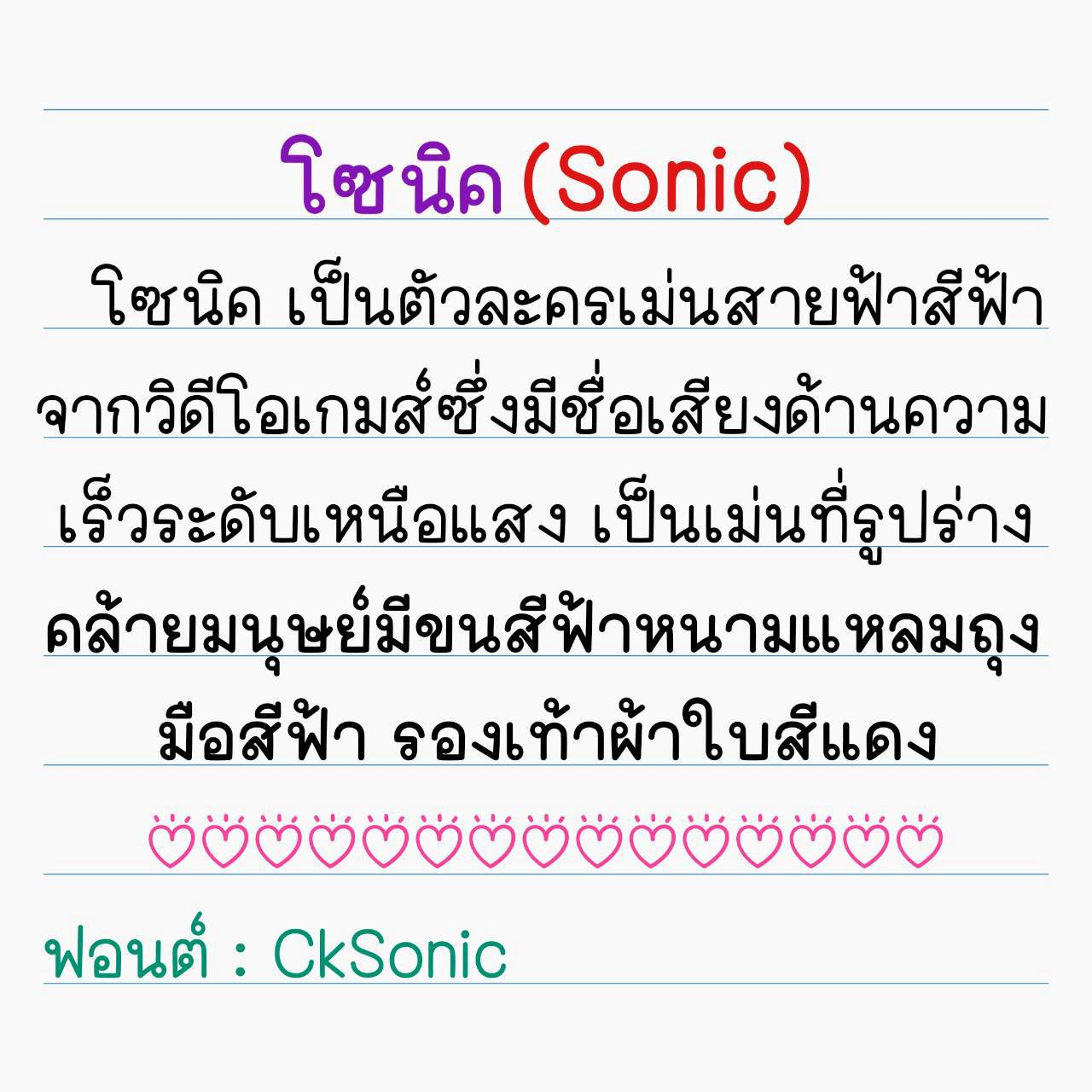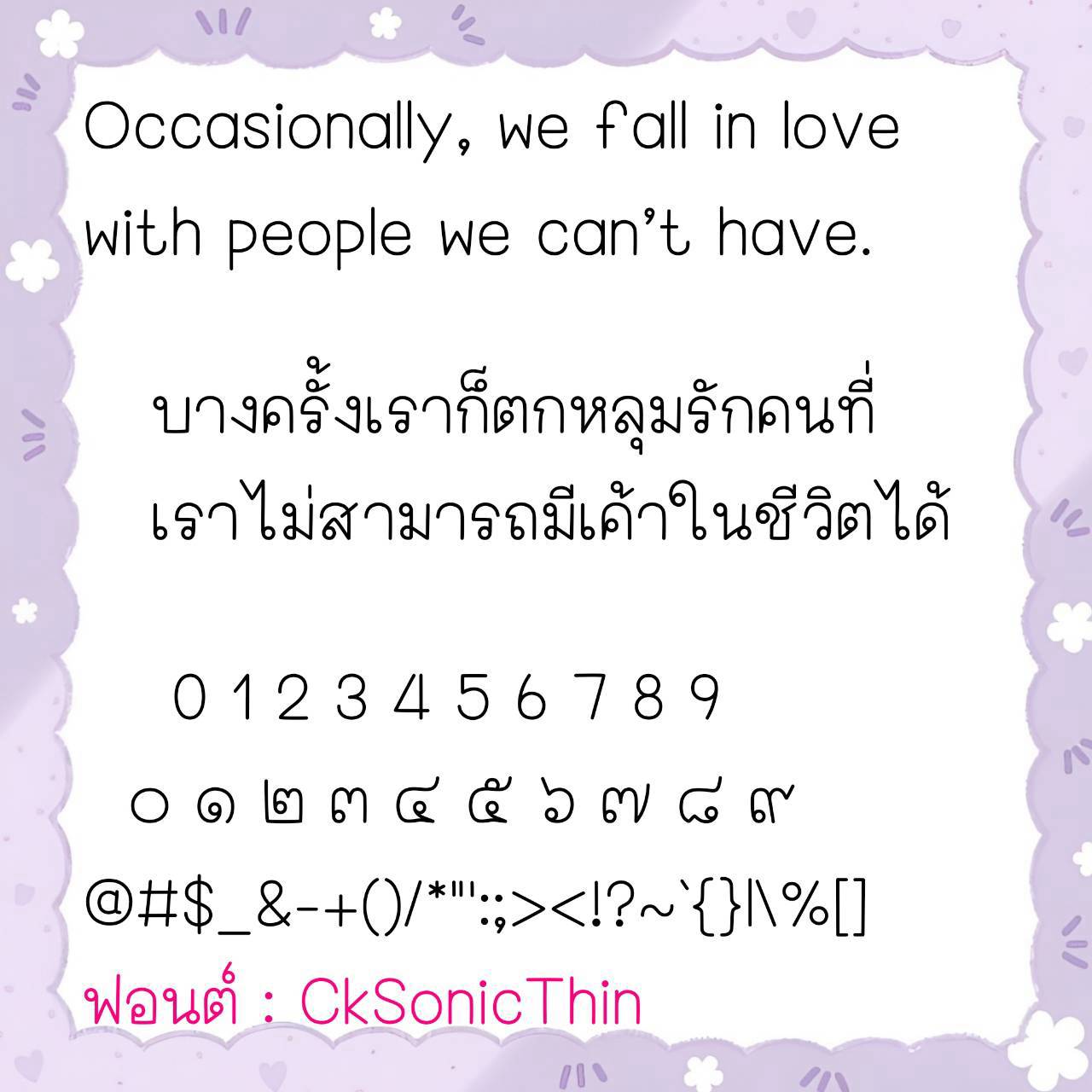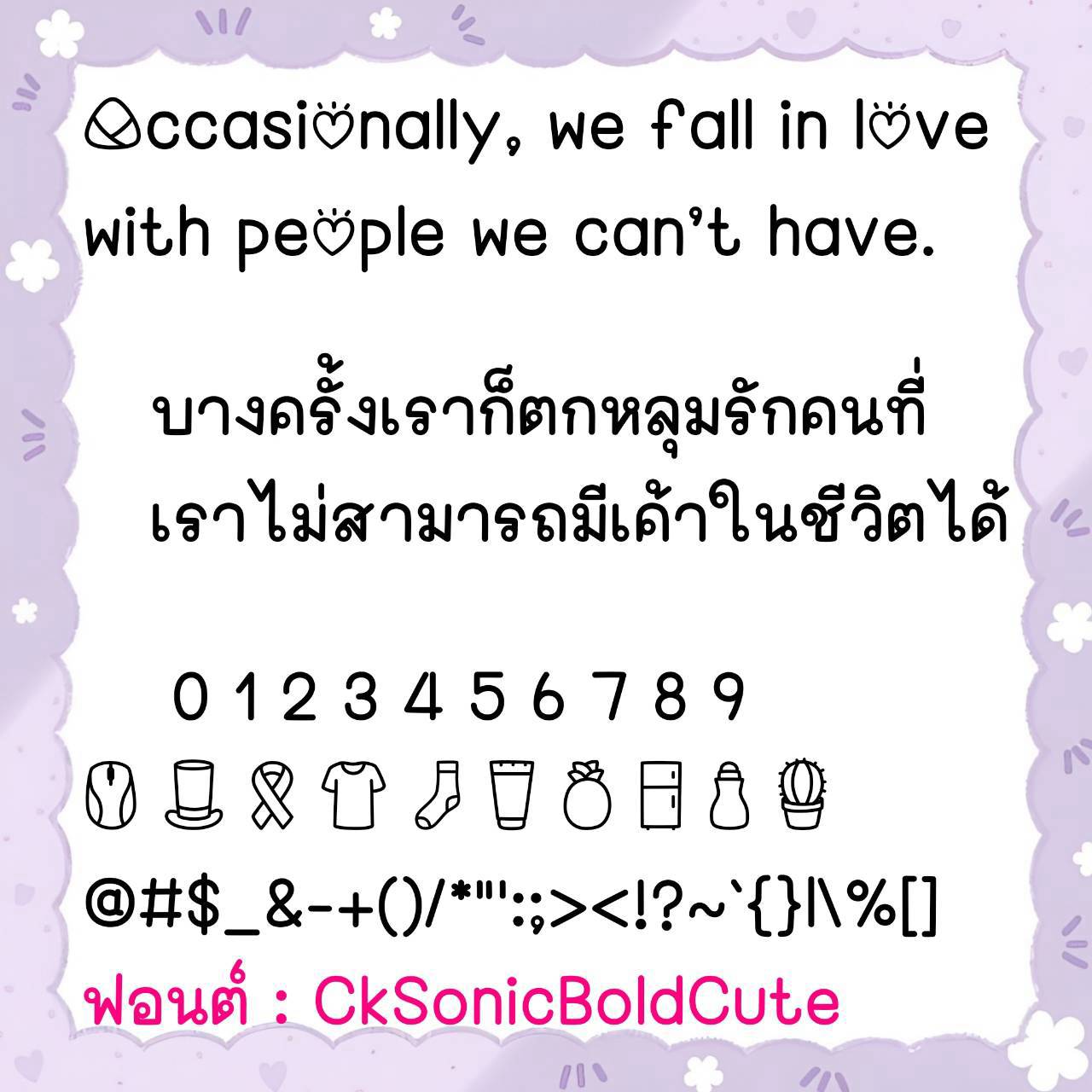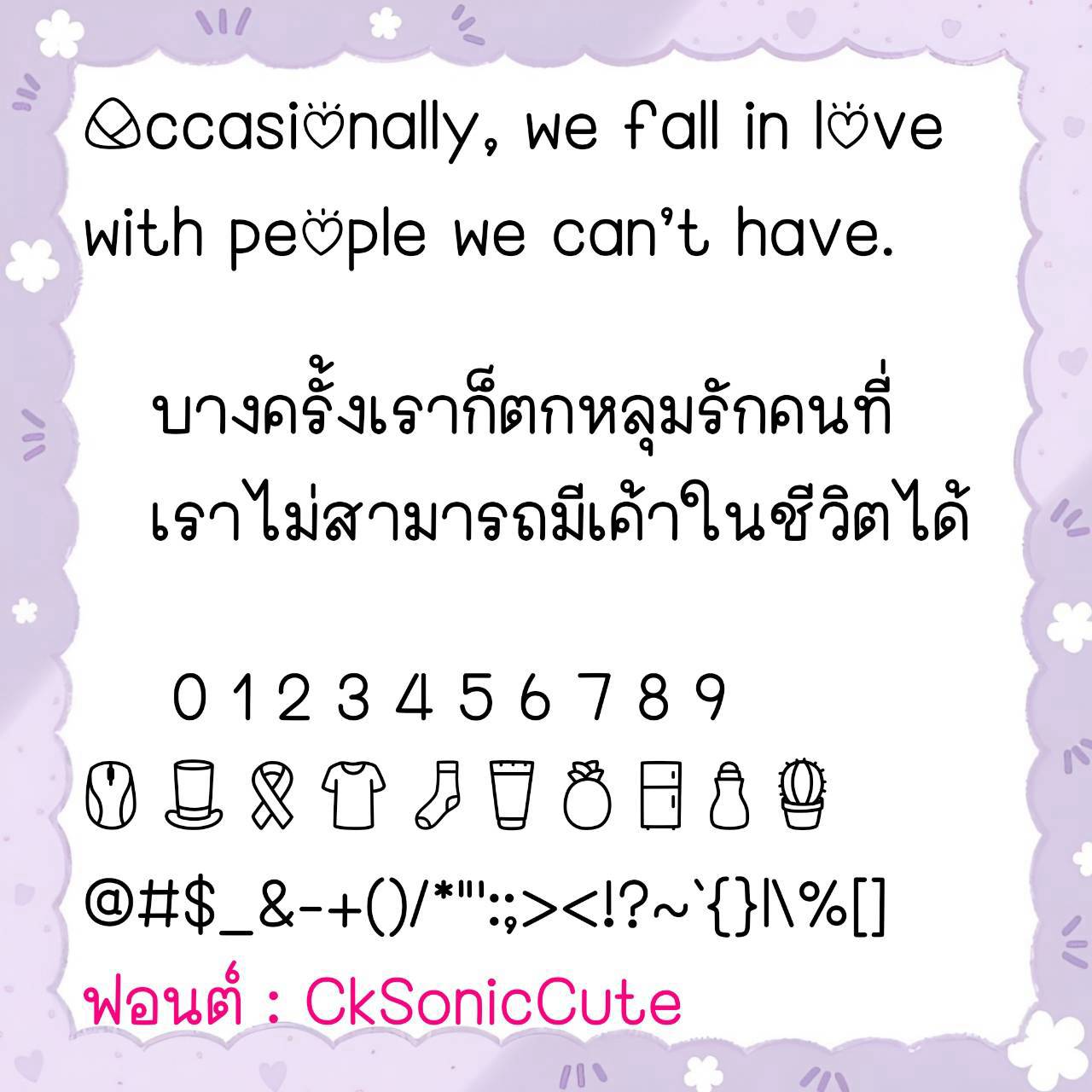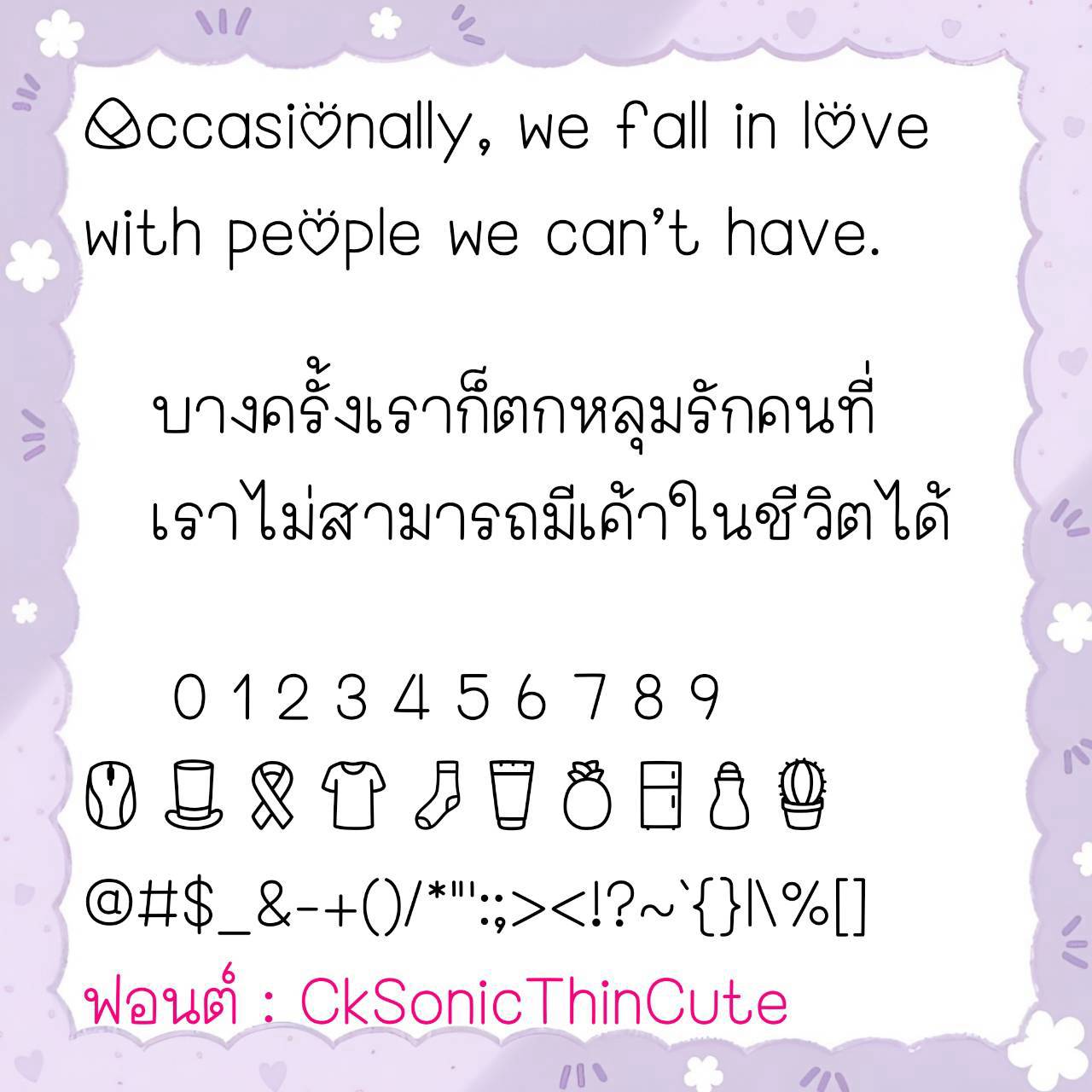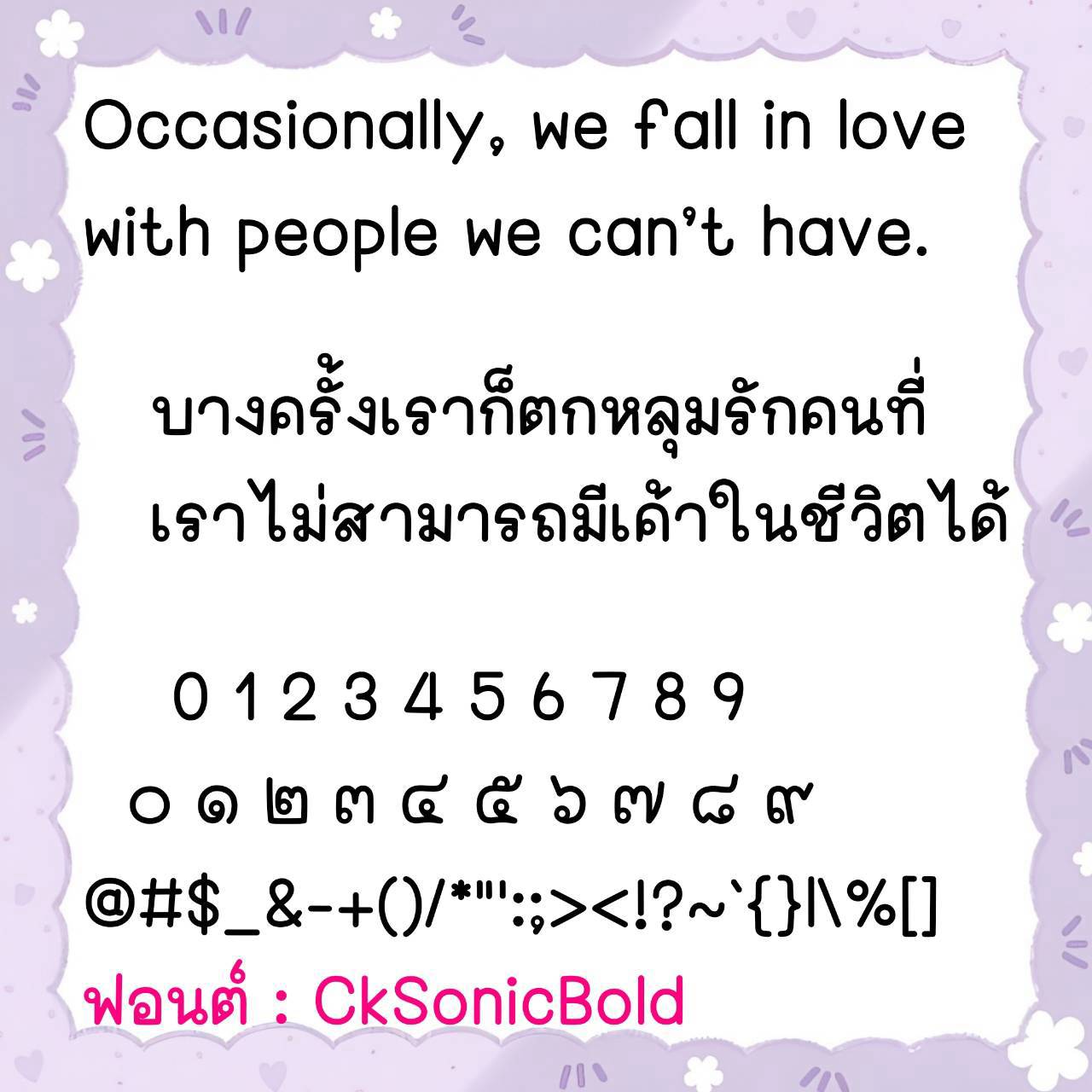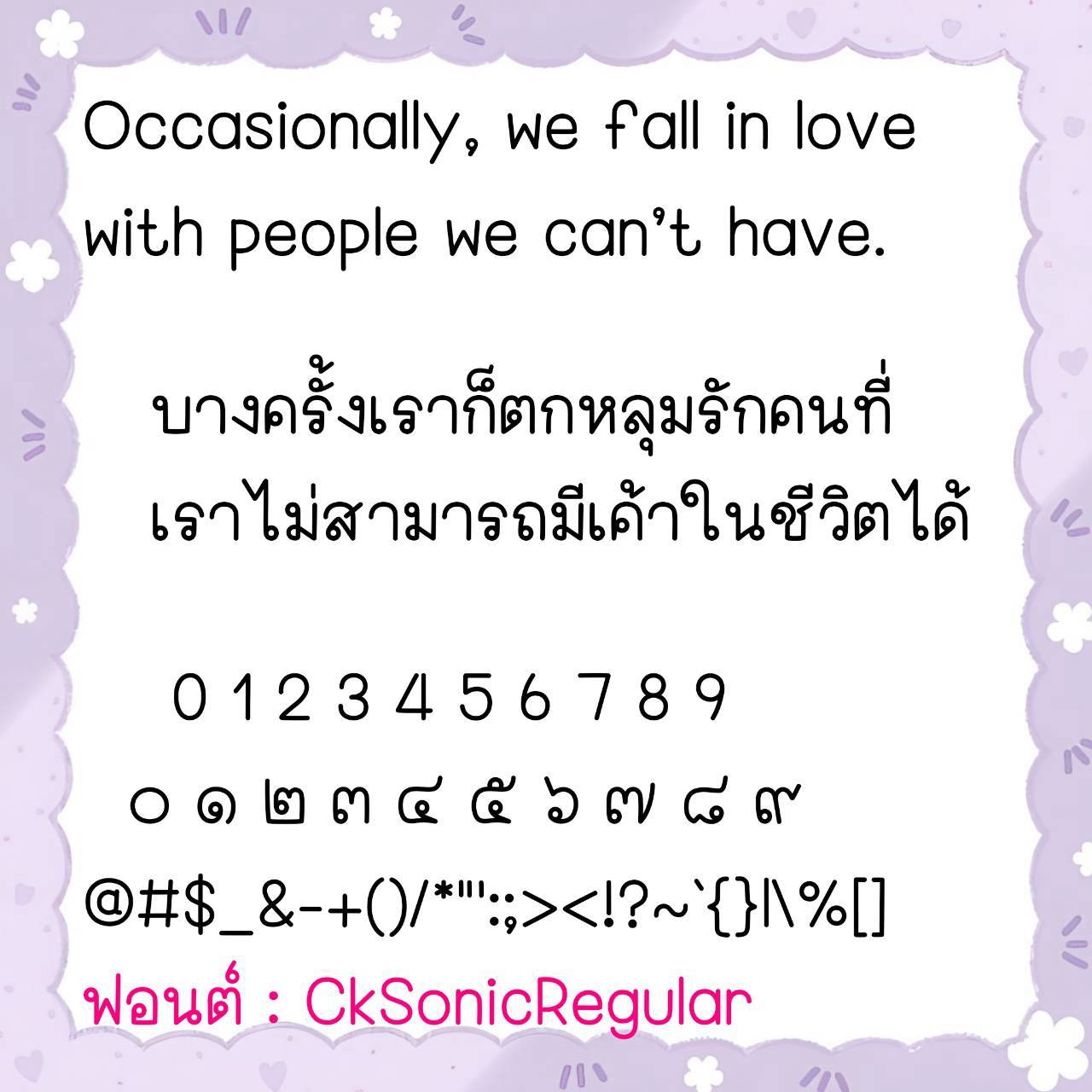
Font CkSonic
🔸 ฟอนต์ลายมือแนวเรียบร้อย ตัวอวบอ้วนอ่านง่าย เน้นความเป็นระเบียบมากๆ เพื่อให้ใช้งานง่ายสะดวกสบาย และยังมีไฟล์อิโมจิน่ารักๆที่ใช้แทนเลขไทยให้ด้วยค่ะ 🥰💙
🔹 This is a neat, handwritten font with chubby, easy-to-read characters. It emphasizes orderliness for ease of use and convenience. It also includes cute emoji files to replace Thai numerals. 🥰💙